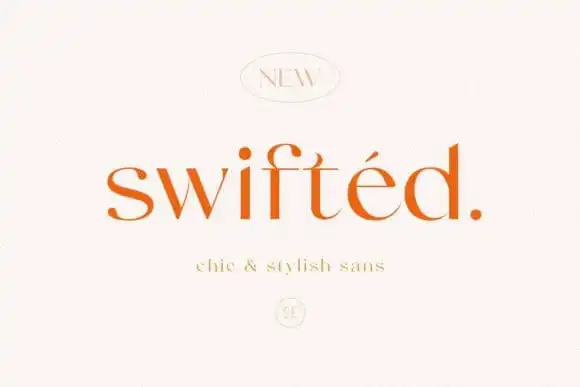
Swifted Serif Font – Download Grátis
Swifted Serif é uma elegante e única fonte com setas que as letras se ligam suavemente. Esta fonte funciona melhor em tamanhos maiores, ideal para headlines, títulos ou textos curtos. Você pode apreciar os belos detalhes em qualquer caractere que tornará a fonte mais fashionista ainda. Swifted também contém uma quantidade impressionante de ligaturas essenciais que irão fazer sua apresentação ou logomarca ainda mais impressionante e destaca-se! Esta fonte suporta várias linguagens e já está codificada com PUA.